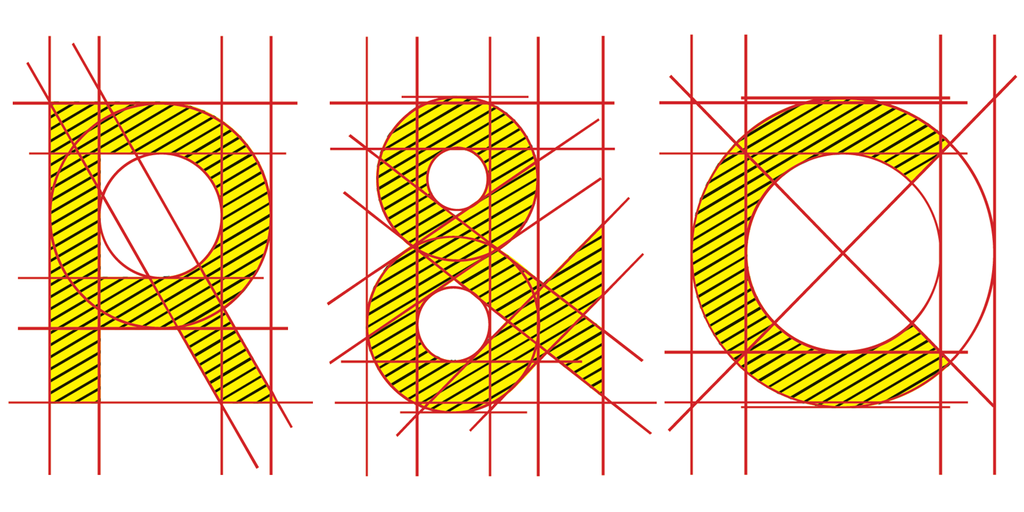
R&C Font
A fonte R&C é uma criação meticulosa, totalmente feita com uma régua e uma seta compasso. Suas linhas precisas são ideais para desenho técnico ou qualquer aplicação que exige um grau de precisão raro em outras fuentes digitais. Como a descrição original indica, ela é gratuita para uso pessoal. Para obter a versão completa com oito estilos ou uma licença comercial, visite o site www.myfonts.com/fonts/jbfoundry/r-c/. Este design cuidadoso e detalhado de Hamilton oferece não apenas aparência precisa e clara, mas também um toque especial que torna R&C perfeita para trabalhos profissionais.